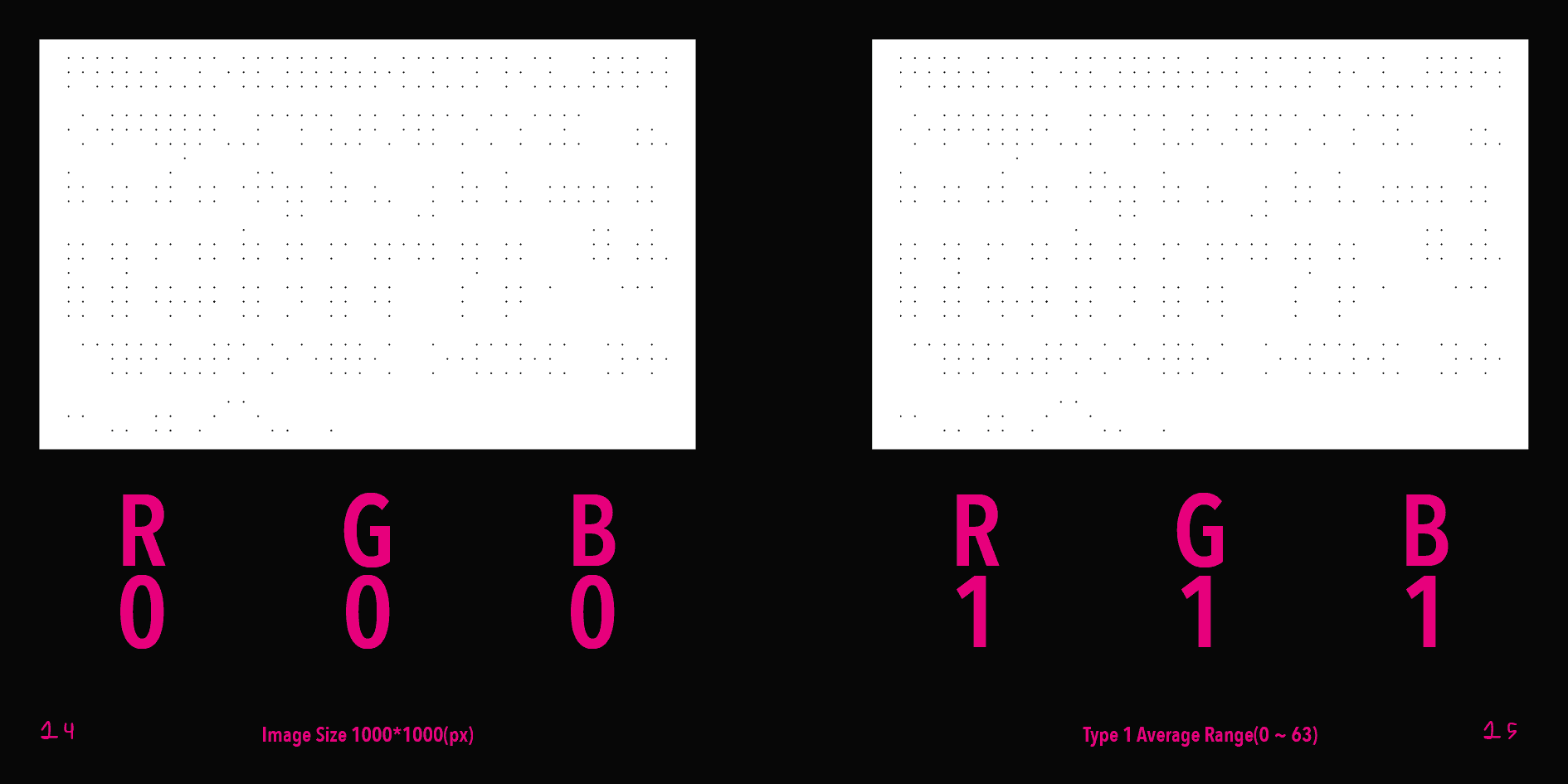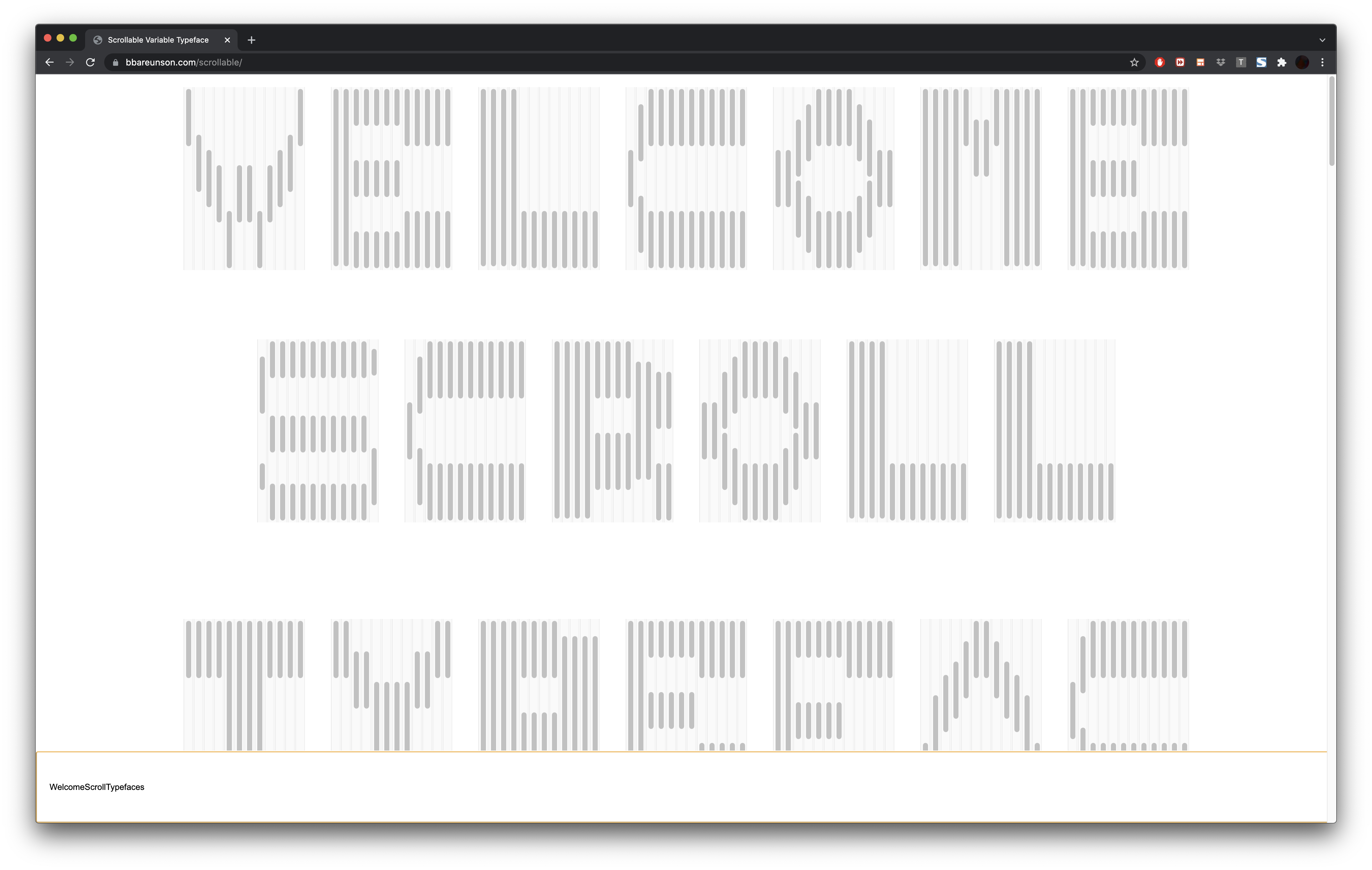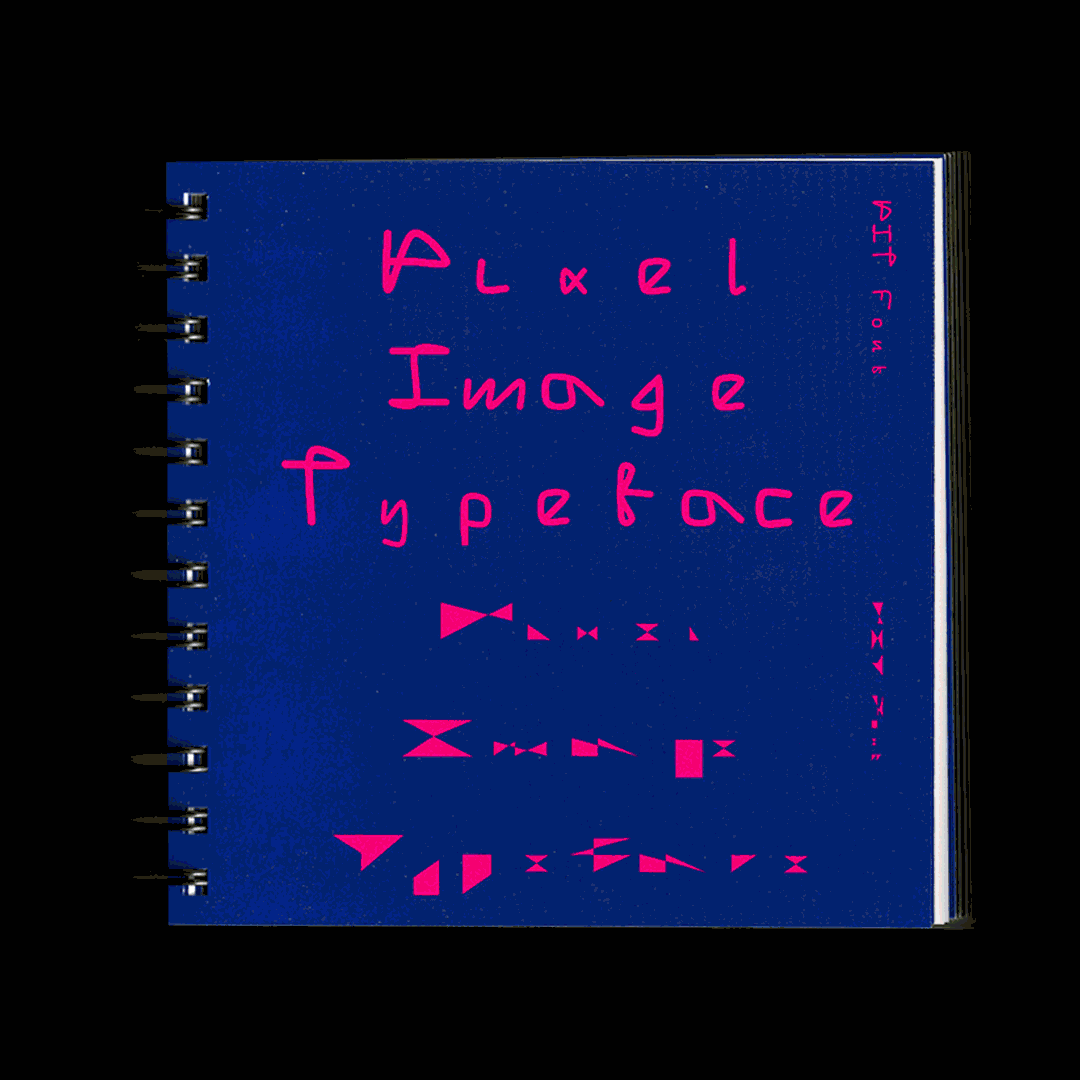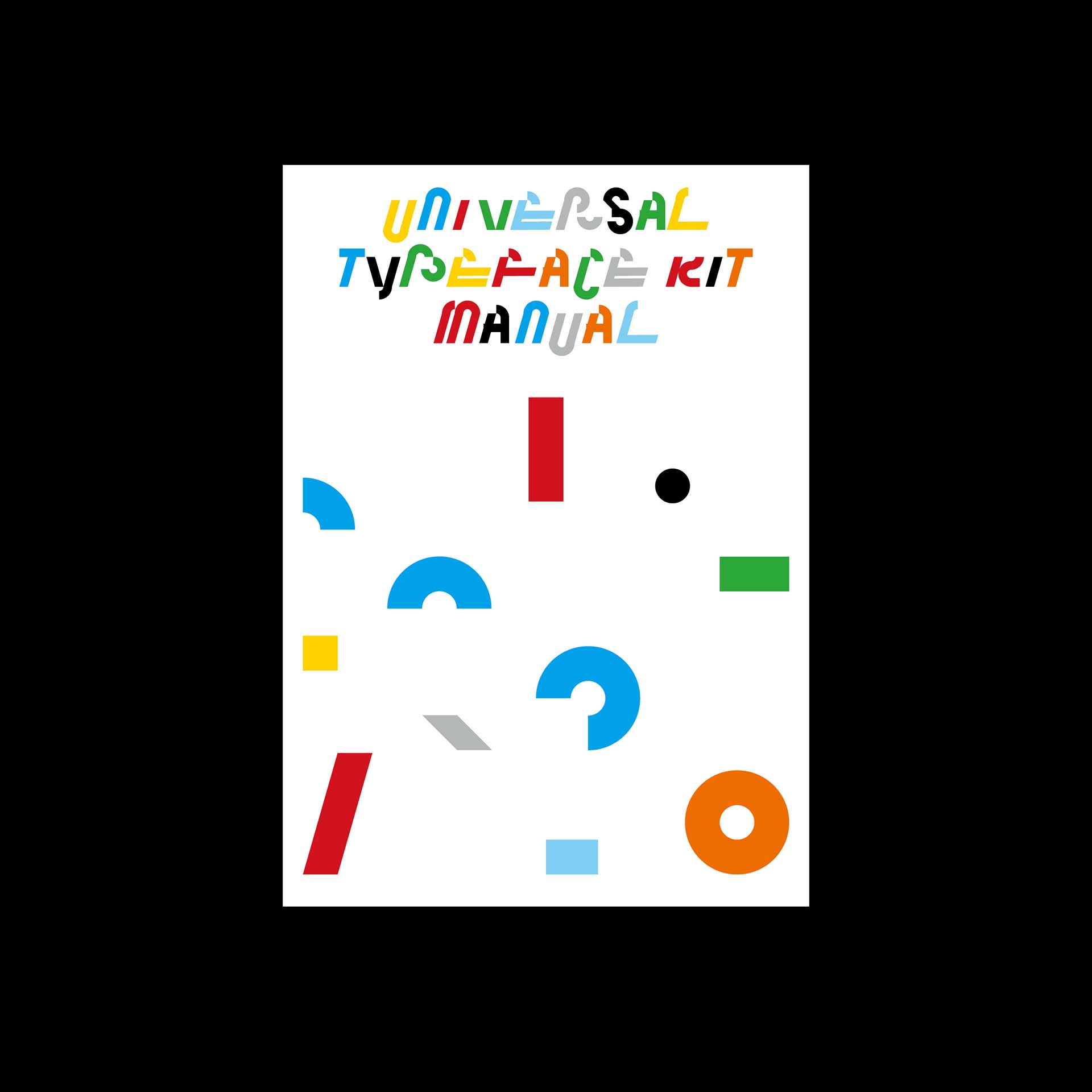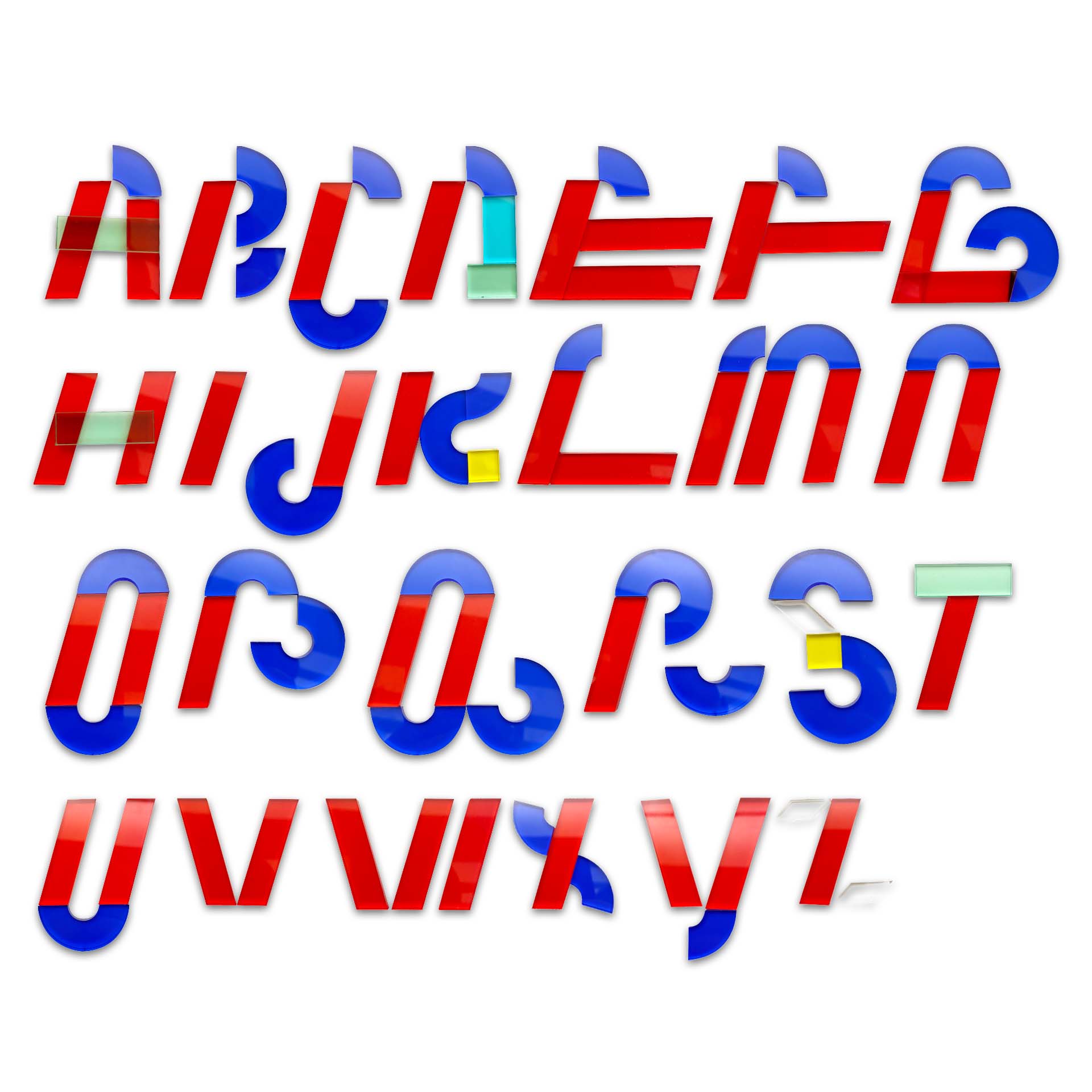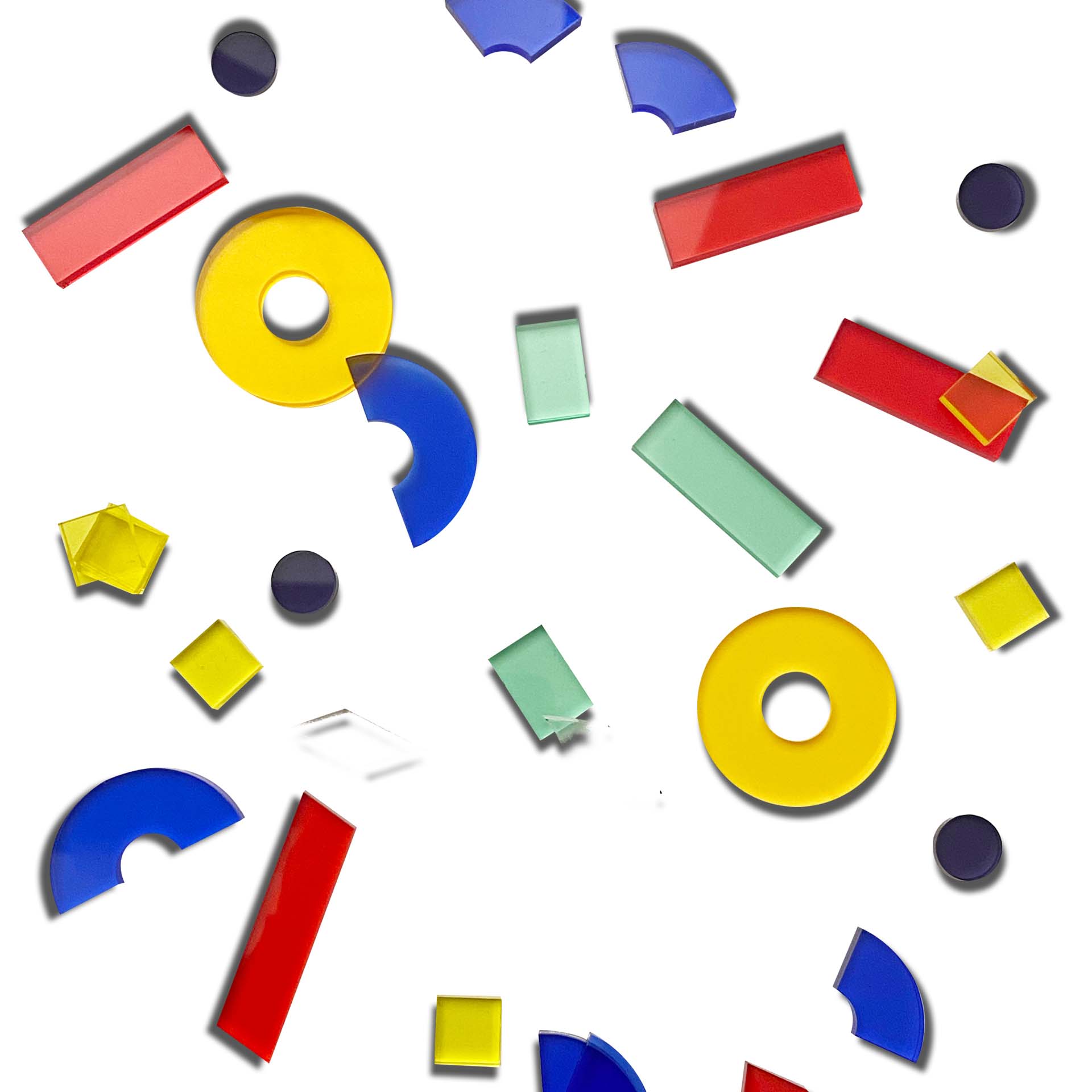
[크리에이터를 만나다] 웹, 그래픽, 폰트를 아우르는 다재다능 ‘빠른손 스튜디오’ 김도현 디자이너
"인쇄 매체 디자인에서의 컨디션처럼 디지털 매체 안에서의 컨디션을 인지하고
둘을 섞어서 재매개(remediation)하여 하나의 작업 방식으로도 활용할 수 있다는 점에서
웹 언어와 디지털 매체에서 배포되는 현상을 이해하는 것이 중요하다고 생각합니다."
-
그래픽 디자이너이자 웹 퍼블리셔로 잘 알려진 ‘빠른손 스튜디오’ 김도현 디자이너의 흥미로운 폰트 작업에 초점을 맞춰서 이야기를 나누었습니다.
스튜디오 빠른손 로고
안녕하세요, 스튜디오 빠른손의 간단한 소개 부탁드립니다.
안녕하세요, 그래픽 디자인과 프론트엔드 개발 스튜디오인 ‘빠른손’을 운영하고 있는 김도현입니다. 2018년부터 시작하여 ‘빠른손’이란 이름으로 활동하기 시작한 것은 2019년부터입니다. 아이덴티티 디자인과 책 디자인부터 웹사이트 디자인 웹 개발, 인스타그램 탬플릿까지 인쇄 매체와 디지털 매체로 배포되는 모든 작업을 진행하고 있습니다.
'Oblique Font'
'PIT(Pixel-Image-Typeface)'
'Scrollable Typeface'
인스타그램에서 ‘Oblique Font’, ‘PIT(Pixel-Image-Typeface)’, ’Scrollable Typeface’를 찾을 수 있었습니다. 단순히 흑과 백의 글자 디자인을 넘어서서 사용자와의 인터랙션까지 고려한 점이 놀라웠는데요, 그 중 몇 가지를 소개해 주세요.
⟨Oblique Fonts⟩는 학부 졸업 전시에 선보였던 작품으로, 창작자라면 모두 공감할 순간인 ‘작업이 하기 싫거나 하고 싶어도 잘 풀리지 않을 때’를 담아낸 폰트입니다. 책상에 앉아 주제를 풀어갈 방법을 적고 있지만 잘 진행되지 않을 때, 턱을 괴고 몸이 점점 기울어지며 적고 있는 글자도 점점 기울어지고 심지어 나중에는 알아보기 어려울 정도의 글자가 적혀 있기도 합니다. 이를 서체에 적용하여 대문자와 소문자 라틴 알파벳, 특수 문자들 모두 12세트로 기울어지게 만든 후, 글자를 적으면 기울어지도록 프로그래밍을 했습니다. 스페이스바와 엔터를 입력하면 다시 초기화가 됩니다.
⟨PIT(Pixel-Image-Typeface)⟩는 ‘프로세싱’이라는 도구를 활용하여 처음 만들어본 작업으로, 한 장의 이미지 안에 있는 모든 픽셀의 색상값의 평균과 높고 낮은 정도, 이미지의 가로 세로 비율 등을 조건으로 프로그래밍하여 글자를 만들어내는 작업입니다. 하나의 알파벳마다 9개의 점을 가지고 있고, 이미지의 가로세로 비율에 따라 점 사이 간격이 달라집니다. 그리고 모든 픽셀들의 색상값을 분석하고 이를 활용하여 4가지의 스타일로 글자를 그려냅니다.
⟨Scrollable Typeface⟩는 익숙해진 디지털 매체의 사용 방식으로 인해 인지하지 못했던, 고정된 모니터 안에서 많은 내용을 보여 주기 위해 고안된 스크롤바의 단순한 사용을 넘어서서 디지털 매체의 가변성을 적극적으로 드러내고자 한 서체입니다. 사용자가 입력창에 글자를 타이핑하면 프로그래밍 해놓은 모습의 라틴 알파벳들이 등장하고, 그 글자는 스크롤바로 만들어져 있기 때문에 언제든 스크롤이나 드래그 앤 드롭으로 글자를 바꿀 수 있습니다.
빠른손의 작업은 폰트를 그래픽이나 폰트 프로그램 내의 기술과 접목시켜 주제를 흥미롭게 풀어낸다는 점이 인상적으로 느껴집니다. 각 프로젝트의 주제를 기획하게 된 계기는 무엇이고, 주제에 어떤 방식으로 접근하시는지 궁금합니다.
학부 때부터 웹 개발에 관심이 생겼고, 이를 적극적으로 그래픽 디자인에 접목시키면서 인쇄 매체와 디지털 매체에서 배포되는 그래픽 디자인의 속성에 대한 관심이 많아졌습니다. 특히 그 중에서 서체는 보여지는 매체의 환경이 많이 달라지고 있던 상황이었습니다. 주로 인쇄 매체 속에 적혀 있는 글자들은 인스타그램이나 웹사이트와 같은 디지털 매체에 담겨 독자들에게 쉽고 빠르게 읽히게 되며, 디지털 기기에서의 읽기 경험이나 디지털 매체만의 가변성을 적용한 “가변 서체(Variable Font)”와 같은 것들이 나오기 시작했었던 때입니다. 이러한 가변성에 흥미를 많이 느꼈었고, ⟨Oblique Font⟩를 통해 처음 프로그래밍으로 변할 수 있는 서체를 만들게 되면서 많은 흥미를 느끼게 되었습니다.
그리고 동대학원에 2020년 입학한 동시에 COVID-19 팬데믹이 시작하게 되며 디지털 매체와 우리의 거리는 더욱 가까워지는 모습을 목격하고 체험할 수 있었습니다. 이러한 상황 속에서 매체를 활용하여 창작하고, 매체를 사용하는 그래픽 디자이너인 저조차도 다소 소극적으로 매체를 ‘바라 보고 있기만’ 하다는 생각이 들어, 그 안에서 볼 수 있는 일시적인 인터페이스나 매체 사용 방식, 혹은 인터페이스가 가지고 있는 상징성을 활용하여 그래픽 디자인의 재료로 활용해보고자 했습니다. 그래서 현재 위치를 알려주고 남은 글의 양을 보여 주는 동시에, 주로 보기만 했던 인터페이스인 ‘스크롤’로 구성된 서체, ⟨Scrollable Typeface⟩를 제작했습니다.
'PIT' 서체견본집
‘폰트는 디자인의 재료로서 다른 디자이너들이 사용함으로서 완성된다’는 어느 디자이너의 말이 떠오릅니다. 빠른손의 영문 서체들이 만약 사용된다면 각각 어떤 매체에서, 어떤 용도로 활약하기를 기대하시나요?
저는 서체만을 만드는 디자이너는 아니기 때문에 서체를 제작하게 될 때는 ‘글자’라는 매체로 표현할 수 있는 맥락이 있어서 서체를 ‘선택’한다고 생각합니다. 이에 맥락을 드러내는 하나의 도구로 활용하고 있어서 그 맥락에 맞는 용례로 적용되는 모습을 볼 수 있다면 좋을 것 같습니다.
⟨Oblique Font⟩는 지루하고 하기 싫지만 해야 하는 상황이 목적일 때, ⟨Scrollable Typeface⟩는 웹에서만 볼 수 있기 때문에 길이가 긴 웹사이트의 메인 페이지에서, ⟨PIT⟩는 기업을 대표하는 이미지나 디자이너의 작업들을 모아서 하나의 이미지로 만든 후 이를 프로세싱으로 서체를 만들어 로고 타입이나 슬로건에 적용되는 모습을 상상할 수 있을 것 같습니다.
'유니버설 타입페이스 키트'
몇 가지의 도형들로 규칙을 세워 영문 폰트를 만들 수 있는 ‘유니버설 타입페이스 키트’를 보면서, 자연스럽게 기하학적으로 디자인된 한글이 떠올랐습니다. 영문 서체를 주로 제작하시는 것 같은데, 추후에 한글을 레터링하시거나 관련 프로젝트를 하실 계획이 있으실까요?
아무래도 한글은 조합형이고, 종류가 너무 많기 때문에 짧은 시간 안에 한글에 적용하기에는 어려운 점이 많아서 라틴 알파벳을 주로 디자인하게 되었던 것 같습니다. 한글 레터링은 작업의 결과 일정이 맞는한 꼭 해보고 싶은 작업 중에 하나입니다. 드러내고자 하는 주제의 방향을 글자의 외형으로, 혹은 글자 자체를 그리드로 활용하여 무언가를 만들어낼 수 있는 기회가 있었으면 좋겠습니다!
프로그래밍을 통해 폰트를 만드는 것은 꾸준한 공부가 필요하고, 트렌드에도 민감해야 할 것 같습니다. 폰트들을 제작할 때 무엇을 가장 중요하게 생각하시는지도 궁금합니다.
타이핑 할 때마다 변화가 생기는 서체를 프로그래밍으로 만들어낼 수 있는 방법을 찾아보니 ‘글립스’라는 프로그램에서 가능하다는 것을 알게 되었습니다. 그래서 구글과 유튜브에서 검색하여 필요한 기능을 하나둘씩 알게 되었습니다. 프로그래밍을 통해 무언가를 만들 때는 트렌드에 민감한 정도도 중요하지만, 개인적으로 오히려 만들고 싶은 것이 확실히 있는 상태가 기능을 습득하고 이를 활용하는데 효과적이라고 생각합니다. 필요한 기능을 차근차근 알아가면서 흥미를 느끼고, 도중에 그만두지 않을만큼의 힘을 얻어야 하기 때문입니다. (개발하면서 한 가지가 잘 풀리지 않으면 모두 그만두고 싶을 때가 많습니다.) 그래서 ‘글립스’를 처음 공부할 때에도 너무 어려웠지만, 처음으로 기울어지는 장면을 만들어낸 순간의 희열을 원동력으로 작품을 끝낼 수 있었습니다.
'Klim Type Foundary' 인스타그램 캡쳐
좋아하는 해외 폰트 디자이너나 파운더리가 있으신가요?
최근 논문을 작성하고 작업하면서 알게 된 타입 파운더리인 ‘Klim Type Foundry’의 서체를 보여 주는 방식을 재미있게 보고 있습니다. 이 파운더리는 서체의 이야기를 영화 같은 웅장한 3D 영상으로 제작해서 선보이는 특징이 있습니다. 서체 디자이너들이 서체를 보여 주는 방식에 있어서 인스타그램에서 글자의 특징을 드러내는 이미지나 광고 문법을 적용한 영상을 주로 선택했다면, 클림 타입 파운더리는 디지털 매체 속에서 쏟아지는 이미지와 영상 속에서 서체 프로모션의 과장되면서도 세련된 모습을 보여 주고 있어 주로 찾아보고 있습니다.
'D-IDOL'
이번에 새로 기획하신 D-IDOL에 대해서도 간단한 소개 부탁드립니다.
⟨D-IDOL⟩은 대문자 라틴 알파벳 26개 각각 한 명의 멤버로서 활동하고 있는 가상의 K-pop 타입페이스 아이돌입니다. 이들은 디지털 매체에서만 볼 수 있는 ‘필터’라는 개념을 거친 후의 모습을 상상하며 디도(Didot)라는 서체를 변형해 만들었습니다. 그들의 데뷔 앨범인 ⟨SPHINX OF BLACK QUARTS JUDGE MY VOW⟩(검은 석영의 스핑크스, 내 맹세를 판단해)는 26명의 멤버가 모두 들어갈 수 있도록 모든 알파벳이 한 문장에 들어 있는 ‘팬그램’ 중에서 그들의 금속 질감과 메인 색상인 검은 색과 잘 어울리는 문장을 인용했습니다.
이들은 K-pop 아이돌로 활동하고 있기 때문에 현존하는 아이돌 산업의 문법을 그대로 가져왔습니다. 그룹의 이름은 “Didot IDeOLogy”로 디도의 사상이라는 뜻과 함께 “Direction to Idea, Destiny, Obviousness and Love”의 앞글자를 따왔습니다. 또한 버벌 네이밍으로는 “The Idol”로도 불릴 수 있기 때문에 “당신이 찾던 바로 그 아이돌이다”라는 뜻을 내포하기도 합니다. 일상 사진을 담은 포토 카드와 함께 앨범마다 존재하는 콘셉트 포스터를 어플리케이션으로 제작했습니다. 또한 한국 아이돌 산업의 가장 큰 특징인 ‘세계관’을 형성하여 이들의 포부를 담은 세계관 영상 또한 볼 수 있습니다.
D-IDOL 기획 마지막에서는 ‘Direction to~’로 D-IDOL들이 사상과 운명, 명확성과 사랑을 향해 활동한다는 포부를 드러내셨습니다. 혹시 디자이너 김도현의 앞으로의 Direction은 어떤 것일까요?
그래픽 디자이너로 일하면서 안정성과 전문성을 계속해서 높여나가고 싶습니다. 어떠한 주제에도 자신 있게 나만의 방법으로 일을 해나갈 수 있는 안정적인 상태를 유지하면서도, 단순히 머무르기보다 모르는 것이 있으면 공부해서 체득하고 하고 싶은 것이 있으면 기반을 갈고 닦아 전문적으로 해낼 수 있기 위해 고군분투하고 있습니다. Direction으로 비유하자면 일방통행보다는 원형 교차로라고 생각할 수 있을 것 같습니다. 계속해서 돌아갈 수도 있고, 언제든 어떤 곳으로든 나가서 새로운 것을 바라볼 수 있으니까요!